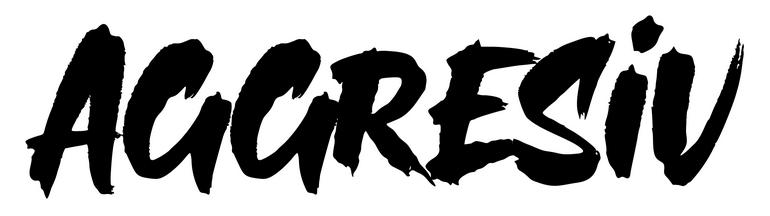
Krakenstein eine aggresive Schrift?
Findet ihr, dass die Krakenstein auch als "aggresive" Schrift genutzt werden kann?
Die kann sogar als "aggressive" Schrift genutzt werden. :rockon:
Nee, im Ernst, das hängt auch immer von der umgebenden Gestaltung ab. Die Schrift selbst eignet sich aber grundsätzlich für Horror oder Aggression, auch wenn nur ein friedlicher Begriff gesetzt wird. Ich liebe die Zähne des C …
Vordergründig aggressiv finde ich sie jetzt nicht unbedingt. Ich denke auch, dass da wohl mit weiteren Stilmitteln nachgeholfen werden müsste.
Habt ihr denn eine andere Idee, welche Schrift passen könnte?